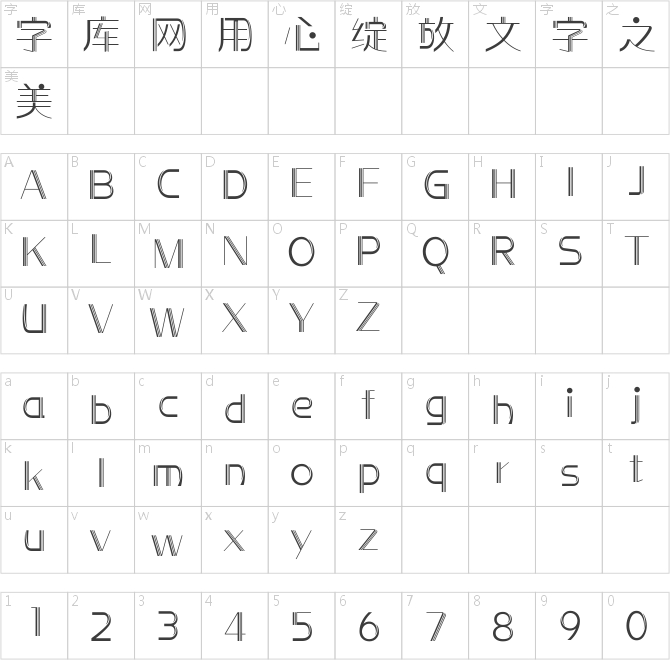
字體名稱: 方正前衛(wèi)體 簡
方正前衛(wèi)體 簡 Light
方正前衛(wèi)體 簡 Light介紹
方正前衛(wèi)體 簡 Light字體字庫是一款讓人賞心悅目、百看不厭的中文字體,適合各類廣告和產品包裝設計應用,字體大小3.06MB,格式為ttf字體,上傳用戶是素年錦時,作者/版權方為方正字庫